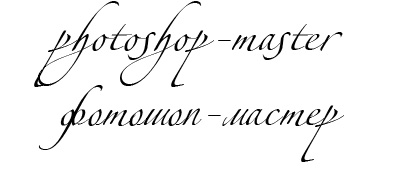
Шрифт - Zeferino
Интересный шрифт, который хорошо подходит для работы в фотошопе. Есть поддержка русского языка.
Внешний вид:
Интересный шрифт, который хорошо подходит для работы в фотошопе. Есть поддержка русского языка.
Внешний вид: